今回は、文字の中に「星」のイラストやモチーフが入っている星入りデザインのフリーフォントをまとめてみました。
「星」が入っていることで、文字が印象的になりインパクトが出るので『バナーデザイン』『サムネイルデザイン』『推し活グッズ制作』といった場面で活躍できます。
本記事で紹介しているどのフォントもキラリと光る星が印象的で、見ているだけでもキュンとしてしまうフォントばかりです!
「星」のモチーフが入っているおすすめフリーフォント
以下の画像サンプルは、本記事で紹介しているフォントの一部です。このように文字の中に星のイラストやモチーフが入ったフォントを紹介しています。
タイトルロゴや見出しなどにぴったりなフォントです。
カタカナボーイ
カタカナボーイフォントは、少年が冒険心をくすぶるような元気な印象があるカタカナフォントです。カタカナのみのフォントですが、濁点などに「星」が入っていて可愛いですね★
星の散らばり字
星の散らばり字フォントは、文字に星座や流星が隠れているユニークなデザインフォントです。星と星を繋げると文字が浮かび上がってくる、そんな可愛らしいフォントです。
きらら字
きらら字フォントは、文字の先端に星型のモチーフが装飾されているフォントです。キラッと光る装飾が加えられているのが可愛らしいデザインです。
プラネタリウム
プラネタリウムフォントは、夜空に輝いている星が散りばめられているカタカナ・英字フォントです。「宇宙」や「天体」などを題材としたロゴタイトルなどにぴったりハマるフォントです。
ぼくらの
ぼくらのフォントは、星をあしらったファンタジー感が満載なデザインフォントです。「悪から世界を守る勇者とその仲間の冒険」をモチーフとしたデザインで、文字からストーリーを感じさせるフォントです。
解星デコール
解星デコールフォントは、星型の装飾ではないですが、クルッとした装飾が可愛らしいです。
数式フォント
数式フォントは、「数式」に関わる記号が文字に隠れているユニークなフォントです。星のモチーフではないですが、天体などをイメージさせるデザインなので、こちらもおすすめです!
まるこいあす
まるこいあすフォントは、漫画・アニメ「恋する小惑星」のロゴを参考して作成されたフォントです。星が流れているような雰囲気があるデザインのフォントです。
叛逆明朝
叛逆明朝フォントは、星型のような飾りが装飾されているデザインフォントです。高貴な雰囲気があり、とっても素敵なフォントです。
ポプらむ☆キウイ
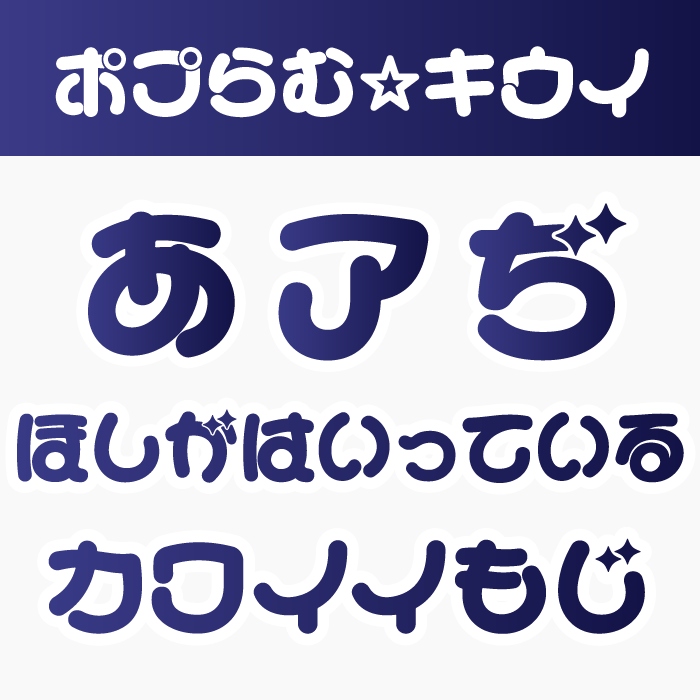
ポプらむ☆キウイフォントは、「濁音・半濁音」の切り替えが可能となっており、星のモチーフが入っている文字と切り替えることができるのがとってもステキです。
きらきらフォント
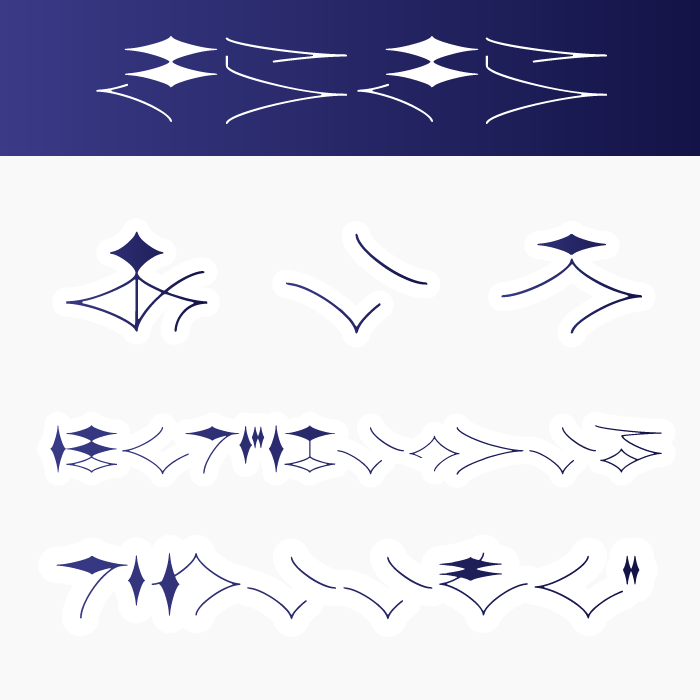
きらきらフォントは、文字というよりまるで記号のような、異世界の言語のような幻想的な雰囲気を漂わせているデザインのフォントです。アクセントやポイントとして使ってみるととってもステキになりそうです。
うたミン-ほし0
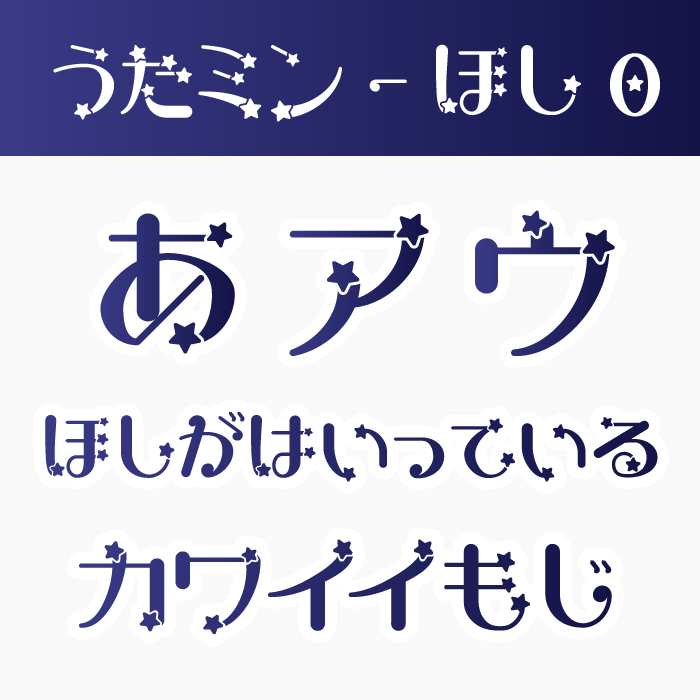
うたミンぼし0フォントは、文字の中に星が散りばめられたユニークでポップなデザインフォントです。